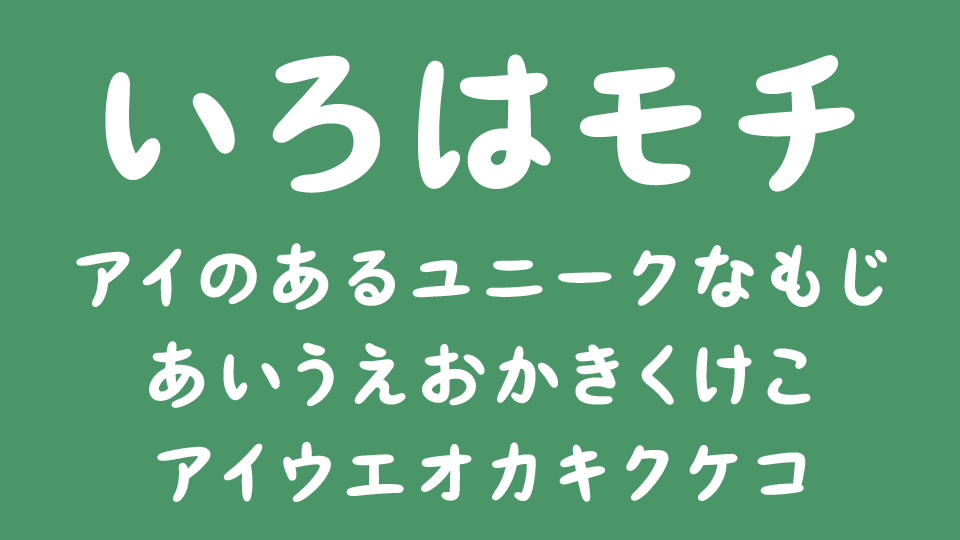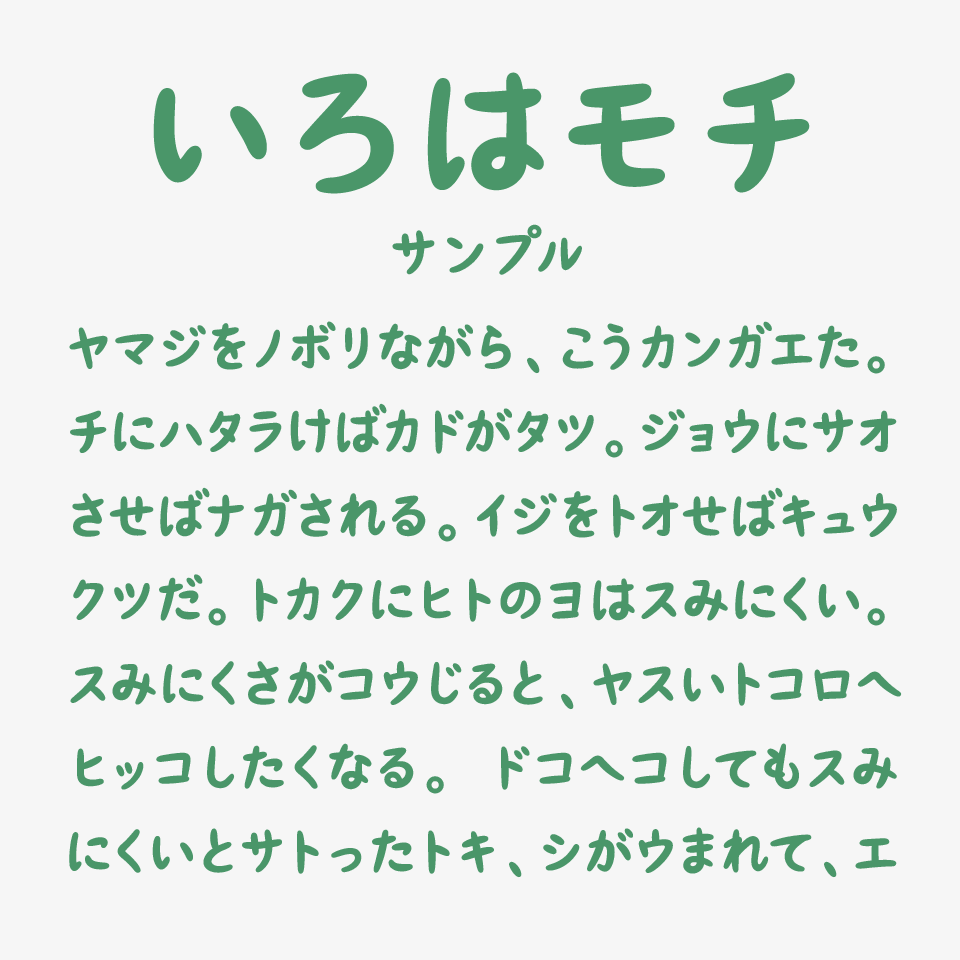
いろはモチ
いろはモチフォントは、モチモチしていてやわらかくて愛嬌たっぷりな可愛いデザインフォントです。
全体に漂う素朴さと、ちょっぴりポップな軽やかさが特徴で、手書きっぽさのあるコロンとした丸みのある文字が、どこかおもちのようにぷにっとしていて、可愛らしいフォントです。
ひらがな・カタカナのみの収録フォントですが、漢字と組み合わせて使いたい場合の混植参考例が配布サイト内で、紹介されているのでぜひ参考にしてみてください。
収録文字は、ひらがな・カタカナ・記号が収録されています。